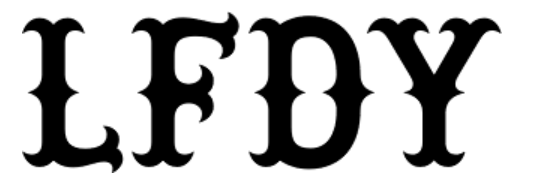
Welche Schrift ist das ? :) (LFDY)
Erinnert mich ein wenig an Hessian, aber irgendwie handgebaut.
wie meinst du das mit handgebaut ?
Dem Logo wird keine Schrift zugrundeliegen, sondern das wird von Hand gezeichnet worden sein. Etwas ungelenk, wie catfonts schon bemerkt hat. Auch die ausgeschriebene Version sieht von Hand gezeichnet aus:
Wobei es eben irgendwie wohl von der Hessian inspiriert war, was diese Gabelungen an den Linienenden betrifft:
Dass hier aber nicht die Hessian verwendet wurde, liegt wohl daran, dass auch dieser Claim nahe an der Philosophie derer liegt, die für ihr CI eben die Hessian einsetzen.